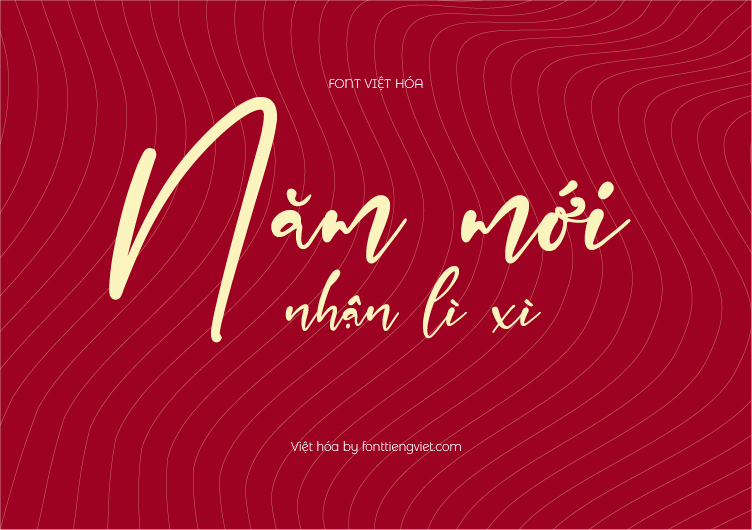
Font Việt hóa 1FTV VIP Smithen Goulding – Tết
Font Việt hóa 1FTV VIP Smithen Goulding – Tết – Đỉnh cao nghệ thuật thiết kế Xuân
Giới thiệu về Font Việt hóa 1FTV VIP Smithen Goulding – Tết
Trong không khí rộn ràng của những ngày cuối năm, việc tìm kiếm một bộ Font Miễn Phí chất lượng để thiết kế bao lì xì, thiệp chúc mừng hay băng rôn sự kiện là ưu tiên hàng đầu của các nhà sáng tạo. Font Việt hóa 1FTV VIP Smithen Goulding – Tết xuất hiện như một giải pháp hoàn hảo, mang đến sự kết hợp tinh tế giữa nét chữ hiện đại và tinh thần truyền thống Việt Nam. Đây là bộ font được tinh chỉnh kỹ lưỡng, hỗ trợ đầy đủ dấu tiếng Việt, giúp người dùng dễ dàng truyền tải thông điệp yêu thương trong dịp Tết Nguyên Đán. Với đường nét uyển chuyển và thanh lịch, bộ font này không chỉ làm nổi bật nội dung mà còn tạo nên dấu ấn thẩm mỹ khác biệt cho mọi tác phẩm đồ họa từ chuyên nghiệp đến không chuyên.
Đặc điểm nổi bật của Font Việt hóa 1FTV VIP Smithen Goulding – Tết
Thiết kế sang trọng và đa dụng
Bộ Font Việt hóa 1FTV VIP Smithen Goulding – Tết sở hữu cấu trúc chữ cái cân đối, với các đường cong mềm mại gợi liên tưởng đến những nét bút thư pháp cách tân. Điểm đặc biệt của nó chính là khả năng thích ứng linh hoạt với nhiều phong cách thiết kế khác nhau. Bạn có thể sử dụng font này cho các tiêu đề lớn trên banner quảng cáo, hoặc dùng trong các đoạn văn bản ngắn trên thiệp mời mà vẫn đảm bảo độ hiển thị rõ nét, dễ đọc. Sự thanh thoát trong từng con chữ giúp không gian thiết kế trở nên thoáng đãng nhưng vẫn giữ được vẻ trang trọng cần thiết cho những ngày lễ hội quan trọng nhất trong năm của dân tộc.
Tối ưu hóa cho tiếng Việt và trải nghiệm người dùng
Một trong những rào cản lớn nhất khi sử dụng font ngoại nhập là lỗi font khi gõ tiếng Việt. Tuy nhiên, với phiên bản Font Việt hóa 1FTV VIP Smithen Goulding – Tết, mọi ký tự đặc biệt và dấu thanh đều được xử lý chuẩn xác, không bị lệch vị trí hay thay đổi định dạng đột ngột. Điều này cực kỳ quan trọng đối với các bạn học sinh và giáo viên khi thực hiện các bài thuyết trình về chủ đề Tết hoặc làm báo tường điện tử. Việc cài đặt font cũng hết sức đơn giản trên cả hệ điều hành Windows và macOS, giúp tiết kiệm thời gian tối đa cho người sử dụng trong quá trình làm việc và học tập sáng tạo.
Ứng dụng thực tế của font trong mùa lễ hội
Sáng tạo thiệp chúc mừng và quà tặng
Sử dụng Font Việt hóa 1FTV VIP Smithen Goulding – Tết để thiết kế thiệp chúc Tết sẽ giúp lời chúc của bạn trở nên chân thành và ý nghĩa hơn. Những nét chữ bay bổng như rồng bay phượng múa sẽ làm cho lời “Chúc mừng năm mới” hay “An khang thịnh vượng” thêm phần ấn tượng. Ngoài ra, các nhãn dán trên hộp quà Tết hay bao lì xì cũng sẽ trở nên cao cấp hơn hẳn khi được trang trí bằng bộ font VIP này. Đây chính là cách đơn giản nhất để nâng tầm giá trị thẩm mỹ cho những món quà tinh thần dành tặng người thân, bạn bè và thầy cô giáo trong dịp đầu xuân năm mới.
Kết luận về bộ font chữ độc đáo này
Tổng kết lại, Font Việt hóa 1FTV VIP Smithen Goulding – Tết là một lựa chọn không thể bỏ qua cho bất kỳ ai đang muốn làm mới diện mạo các thiết kế của mình trong mùa xuân này. Với sự chỉn chu trong từng nét chữ và khả năng hỗ trợ tiếng Việt tuyệt vời, bộ font này chắc chắn sẽ làm hài lòng những người dùng khó tính nhất. Hãy nhanh tay truy cập và tải ngay bộ Font Miễn Phí, Font Việt Hóa, Font Việt hóa 1FTV VIP Smithen Goulding – Tết để bắt đầu hành trình sáng tạo những tác phẩm nghệ thuật đậm chất Tết Việt. Chúc các bạn có những trải nghiệm thiết kế thú vị và một năm mới tràn đầy cảm hứng!